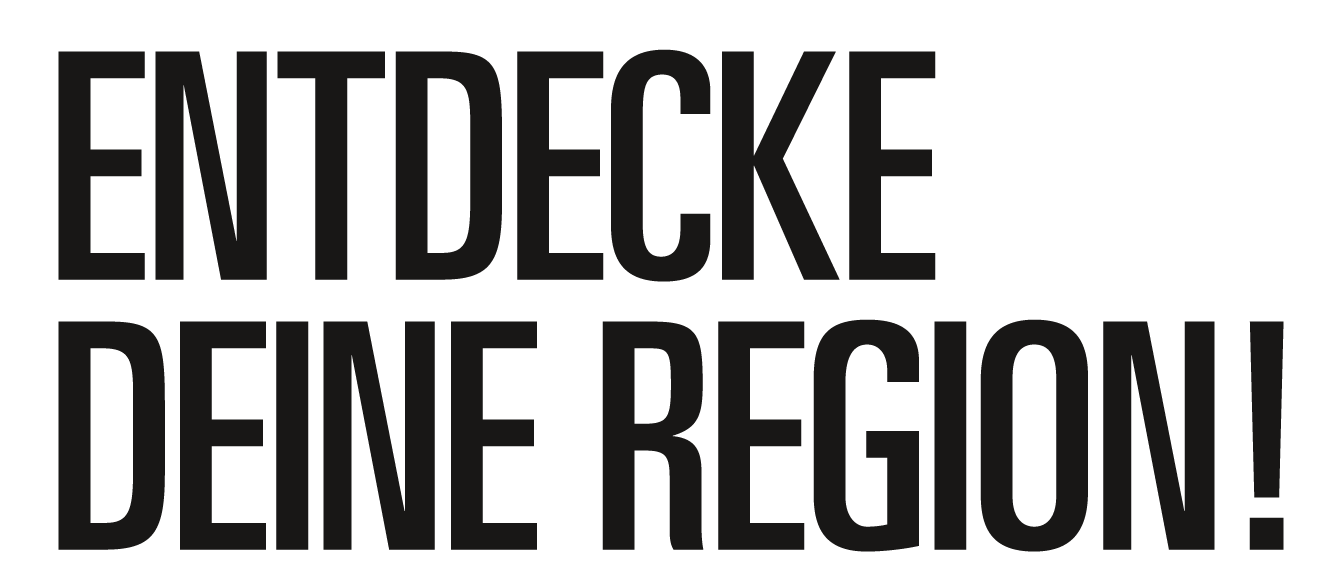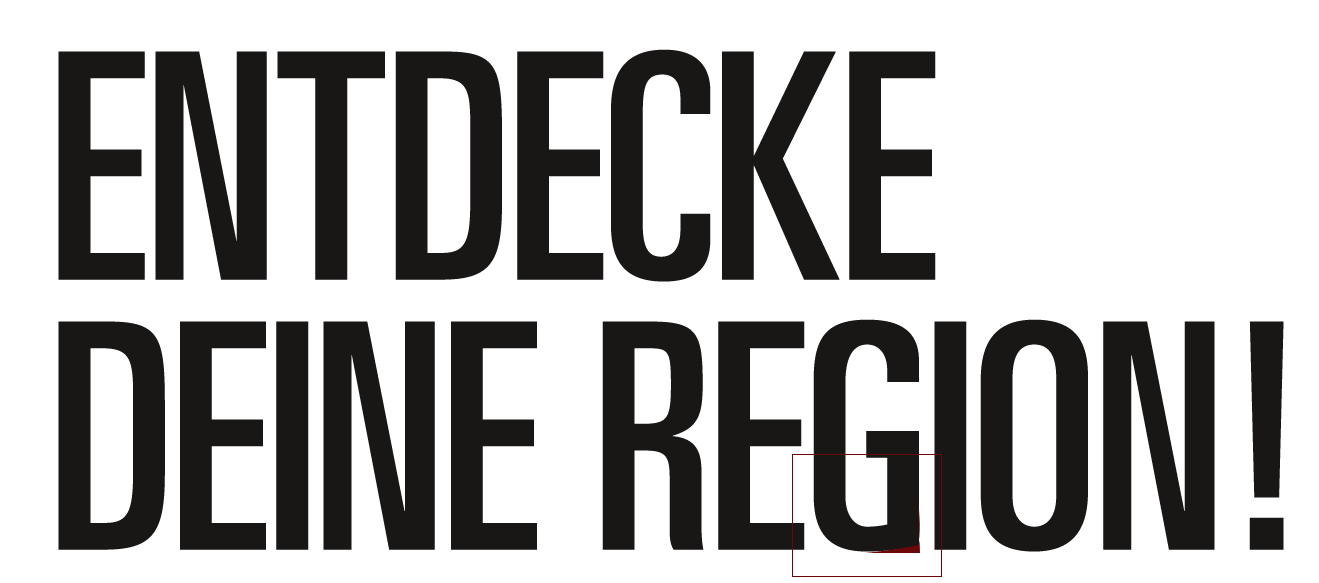
Welche Schriftart ist das? (Entdecke deine Region)
ich benötige Hilfe von den Schriften-Experten und Expertinnen beim Herausfinden der angehängten Typo. Wer hat eine Idee?
Nein, eine Univers ist das nicht. Schau Dir den geraden Grundbalken des »G« an. Der liegt auf der Grundlinie. Spontan hätte ich Akzidenz Grotesk gesagt, aber auch die ist es nicht.
Da bin ich sehr am Zweifeln, weil die Univers nimmte die Rundung auf und geht nicht gerade auf der Grundlinie ein. Das G ist in der Grundlinie nicht geschwungen. Aber vielleicht liegt es ja nur an der Auflösung.
Ja liegt es. Wenn Du Dir Deine Abbildung genau ansiehst, wirst Du an den nach rechts wieder transparent werdenden Pixeln erkennen, dass das G nicht an der Grundlinie kleben bleibt.
:tuschel: Und bertels PDF-Recherche zeigt ja, dass für den Rest der Gestaltung auch die Univers verwendet wurde, insofern passt das schon würde ich meinen. :-)
Ich hab noch ein wenig weiter recherchiert: Die Zielseiten (http://metropolregion.hamburg.de/) verwenden die "Univers Next", die hier aber nicht passt. Das gesuchte Beispiel ist also aus der "Univers".